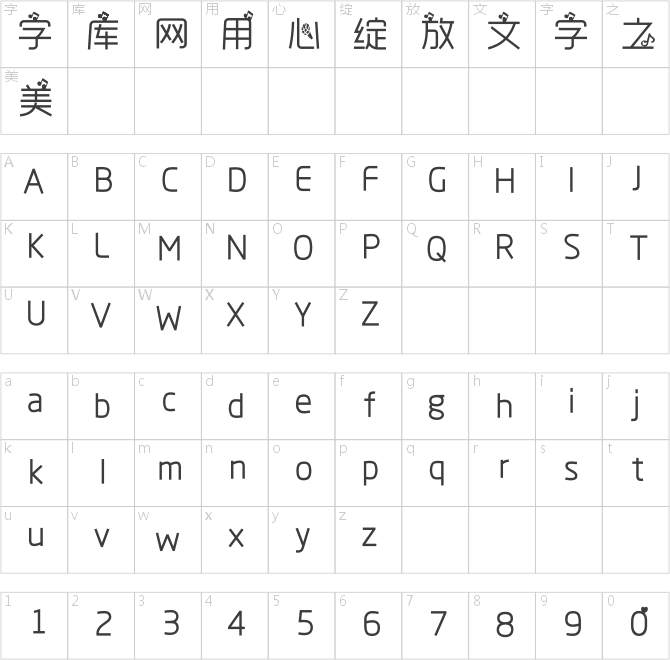
夢(mèng)想家的音符
夢(mèng)想家的音符字體字庫(kù)是一款讓人賞心悅目、百看不厭的中文字體,適合各類(lèi)廣告和產(chǎn)品包裝設(shè)計(jì)應(yīng)用,字體大小14.73MB,格式為ttf字體,上傳用戶(hù)是17199970014,作者/版權(quán)方為未知